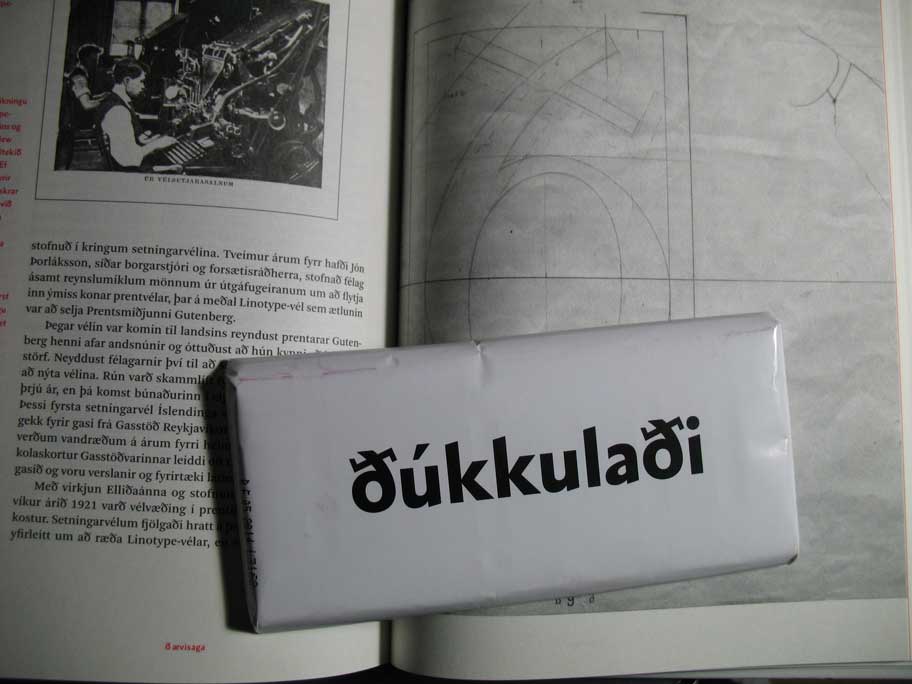
>Comme quoi, la linguistique est une chose trop sérieuse pour la laisser
>à des spécialistes.
> Telle est ma conclusion, et je sais de quoi je parle !
>
Ne pourrait-on pas dire que certains linguistes disent parfois des
« çonneries » ?
Sans parler des jolis thorn et eth, qui enchantent l'oeil du typographe à
chaque fois (même si c'est toute une gymnastique pour les obtenir sur un
mac !)